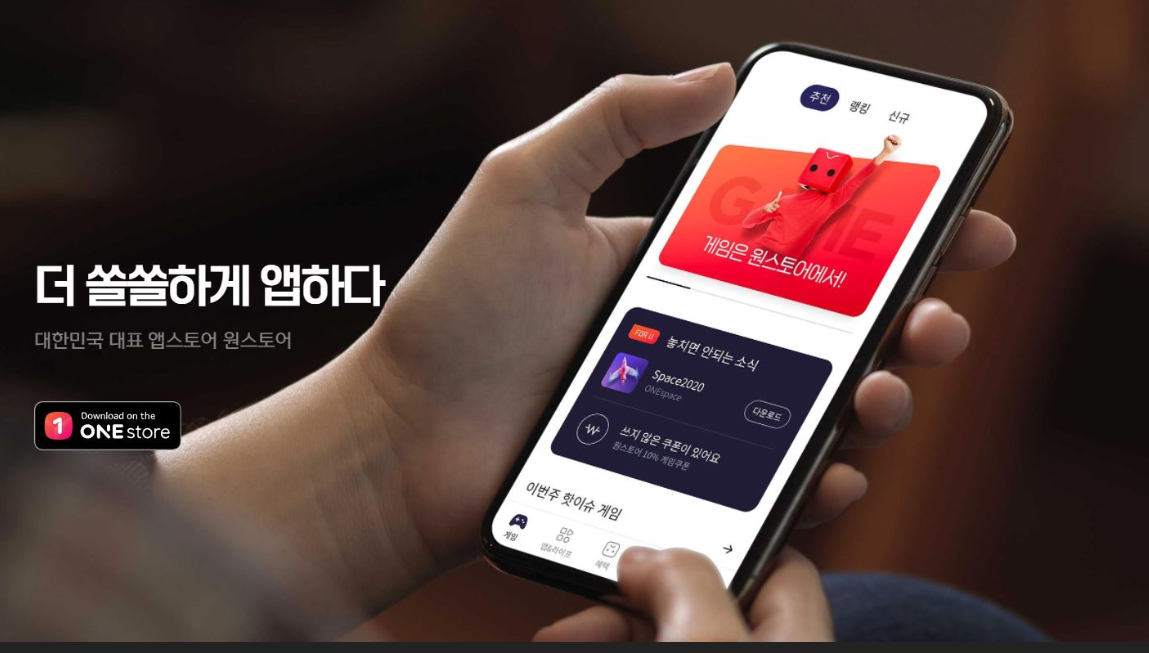
원스토어 모바일고딕 제목체 — (주)원스토어에서 배포하는 무료 폰트입니다. 꽉 찬 ‘ㅇ’과 직선적인 획으로 단단하고 또렷한 인상을 만드는 고딕체
원스토어가 폰트릭스와 함께 만든 서체 가족 가운데 제목을 맡는 쪽입니다.
제작사 설명이 성격을 잘 짚습니다. 베이직한 힘으로 시선을 잡아끄는 제목용 서체로 안정적이며, 단단한 글줄과 부드러운 힘을 가진 자소 디자인을 가지고 있다는 것입니다. 폰트릭스 쪽 보충 설명에 따르면 글자 구조를 단단하고 밀도 높게 잡았고, ㅇ이나 ㅎ처럼 둥근 자소에는 기하학적인 타원 형태를 썼습니다.
굵기는 하나뿐입니다. 그래서 제목과 본문을 한 서체로 해결할 수 없는데, 이는 설계 의도이기도 합니다. 같은 가족에 본문용으로 만든 모바일고딕 본문체가 Light와 Regular, Bold 세 굵기로 따로 있어서 둘을 짝지어 쓰도록 만들어졌습니다. 무료로 쓸 수 있고 BI와 CI, 임베딩까지 되지만 폰트 자체의 수정과 재배포는 금지됩니다.